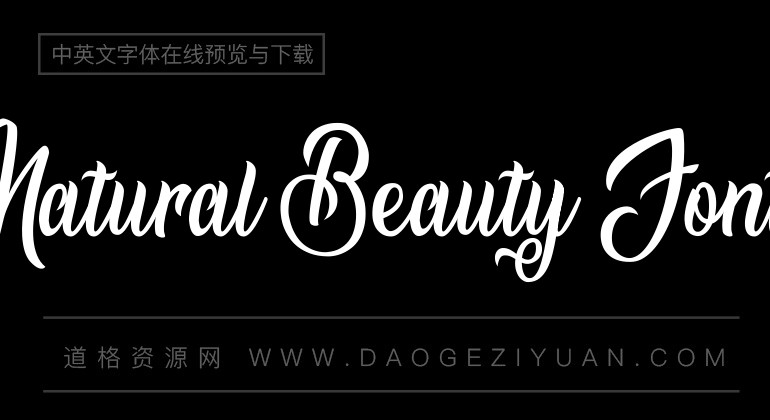
Natural Beauty Font
Natural Beauty Font 是一种手写风格的字体,其特点是自然、流畅、优美。它的字母呈现出不规则的形状,仿佛是人手书写而成。 Natural Beauty Font 适用于各种设计领域,如品牌标识、海报、卡片、宣传册等。这种字体用于设计可以带来一种轻松、自然的感觉,同时也能够吸引人们的目光,从而使设计作品更具吸引力。
Natural Beauty Font是一款非常不错的手写艺术字体,具有很好的视觉感,适合于文化类的宣传设计、商业类品牌的广告和产品包装设计以及个性化文字排版等较多场景。